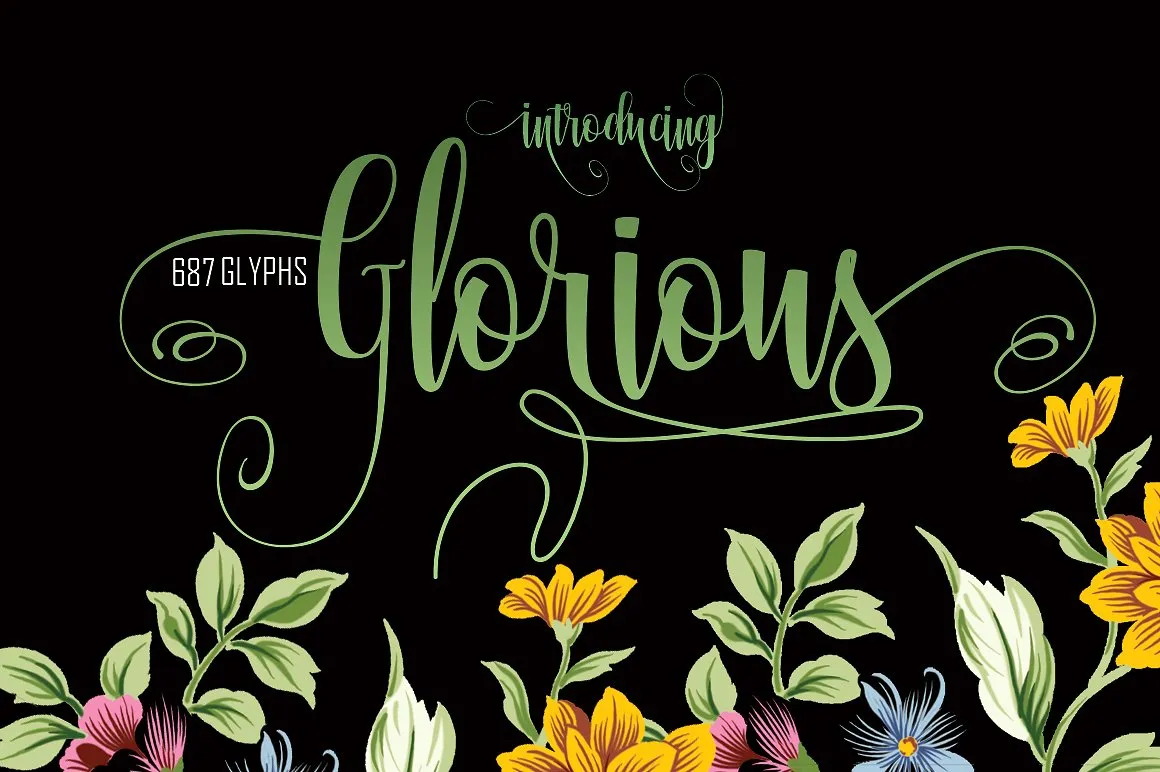
Glorious Script Font – Fonte Grátis
Glorious Script Font
Olá! Estamos muito felizes em apresentar a Glorious Script Font, uma nova opção para designers que desejam dar um toque especial a suas criações. Este tipo de graça moderna é o resultado direto do trabalho artesanal da rtcreative86. Glorious Script font foi criada ao ser escrita à mão e traz formas de calligrafia contemporâneas com um estilo natural, perfeito para uma variedade de usos. Pode ser utilizada em aplicações como headings, logotipos, convites de casamento, camisetas, cartões de correspondência, sinalização, rótulos, notícias, panfletos e até mesmo etiquetas. Nossa fonte traz uma mistura única de modernidade e elegância que é perfeita para qualquer projeto. Seja um trabalho profissional ou artístico, a Glorious Script Font dará um toque especial ao seu design. Descubra por si só como essa font pode transformar suas criações em algo único e inovador.